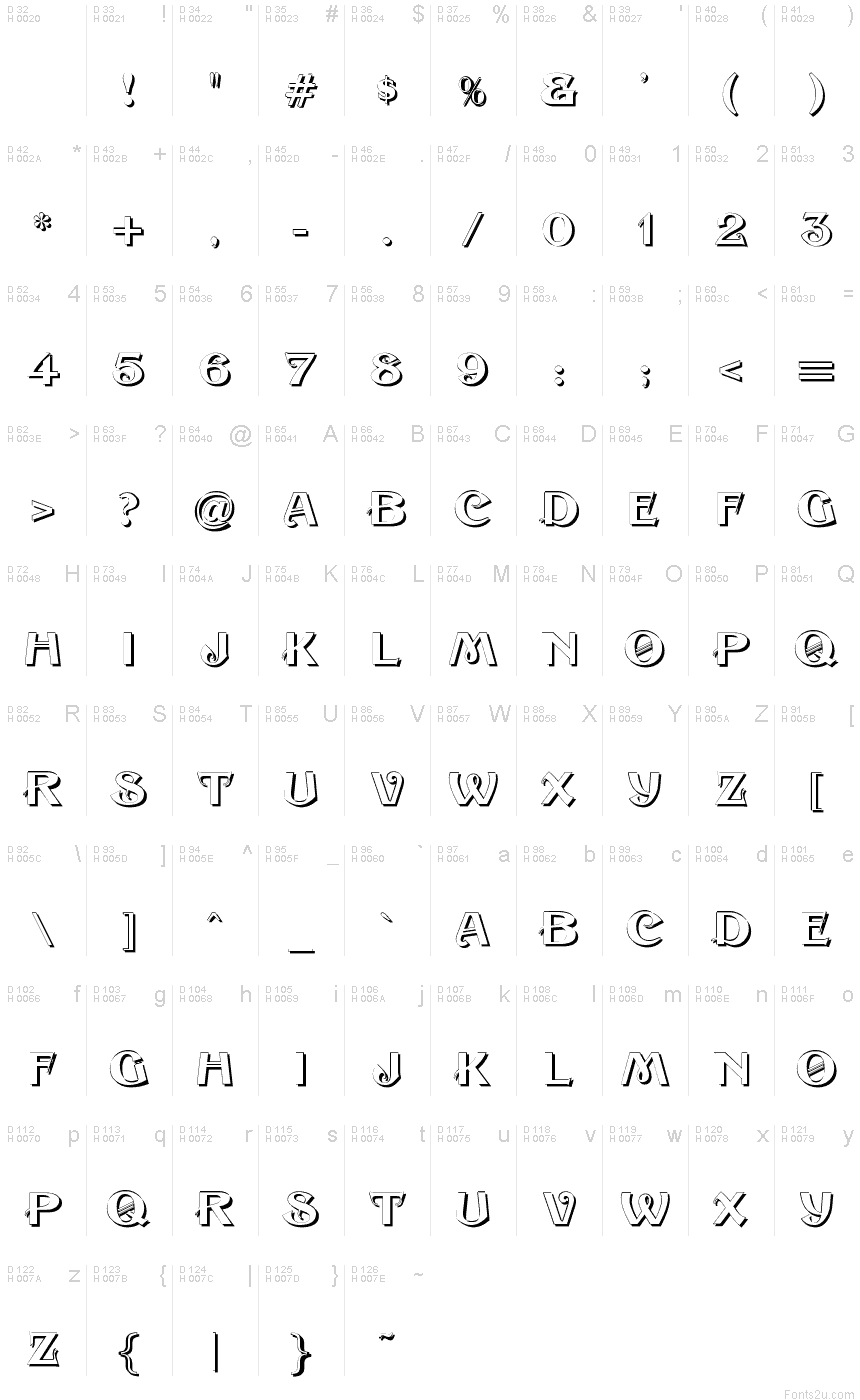
Sesame Shadow
Sesame Shadow od Typographer Mediengestaltung to darmowy, retro font display o swobodnym charakterze szyldów malowanych ręcznie. Wielkie litery wyglądają na szerokie i pełne energii; łączą grube, białe kształty znaków z mocnym czarnym cieniem bocznym oraz kilkoma zakrzywionymi, niemal kreskówkowymi detalami, które nadają alfabetowi żywy rytm sklepowych witryn z lat 50.
Sprawdza się na plakatach, w brandingu w stylu "diner", na okładkach płyt, planszach tytułowych i krótkich nagłówkach opakowań, gdzie ta masywna głębia offsetowa może grać pierwsze skrzypce. Jako darmowy font, jest również odpowiedni do logotypów, monogramów i nagłówków, które potrzebują odważnego, vintage'owego sznytu bez polegania na wytartych teksturach czy tanich sztuczkach.